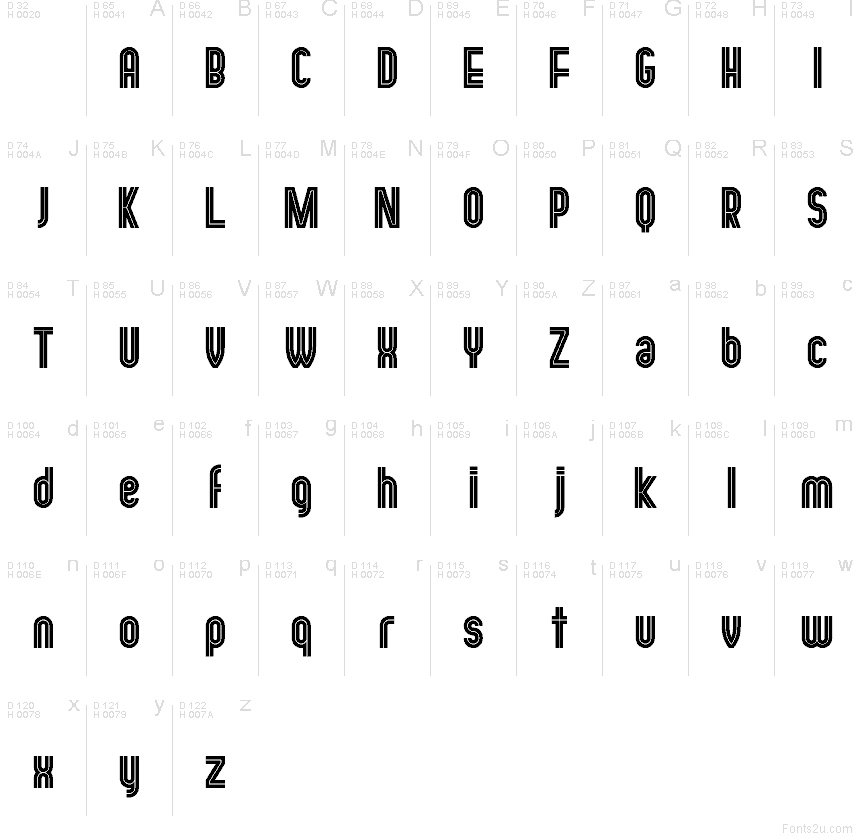
Hofmann Extravagant von Vladimir Nikolic ist eine kostenlose Retro-Display-Schrift mit hohen, schmalen Buchstaben und einem wiederkehrenden Inline-Streifeneffekt, der jedem Strich eine mehrschichtige, posterartige Optik verleiht. Die abgerundeten Ecken und die straffen, gleichmäßigen Kurven sorgen für ein dekoratives Design, ohne dabei den strukturierten, grafischen Rhythmus zu verlieren.
Hofmann Extravagant eignet sich hervorragend für Vintage-Logos, Retro-Verpackungen, Event-Poster, Beschilderungen, Album-Artworks und redaktionelle Titel, bei denen ein komplexer Buchstabenstil das Design maßgeblich prägen soll. Diese kostenlose Schrift bringt genügend Muster und Form mit, um als starker Akzent im Branding zu fungieren, macht sich aber auch auf Etiketten und kurzen Display-Zeilen gut, die eine klare, von den 1970er Jahren inspirierte grafische Behandlung benötigen.
Hofmann ist in den Varianten Regular und Italic erhältlich.